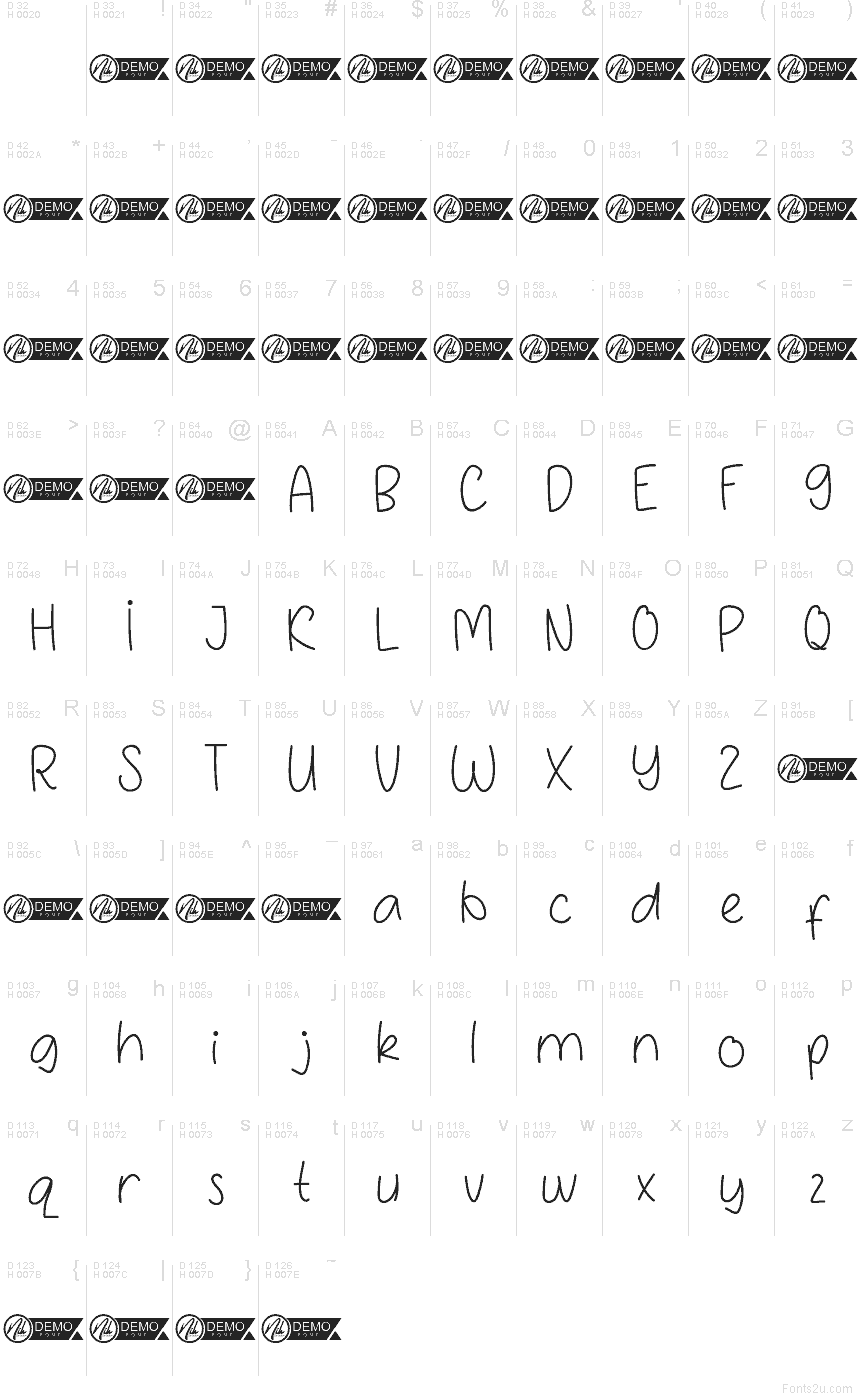
PisangGorengDemo
Pisang Goreng de NihStudio est une police manuscrite gratuite au rythme monolineaire décontracté et aux traits arrondis, offrant un aspect rapide et naturel, comme dessiné à la main. Les formes restent simples et ouvertes, avec des courbes douces et un tracé légèrement irrégulier qui privilégie le naturel à la formalité.
Pisang Goreng est une police gratuite idéale pour les menus de café, les emballages alimentaires, les fiches recettes, les citations sur les réseaux sociaux, les logos décontractés et les titres d'événements. Son style manuscrit apporte une touche personnelle à vos invitations, étiquettes, autocollants ou petits projets de branding sans jamais paraître rigide ou surchargé.